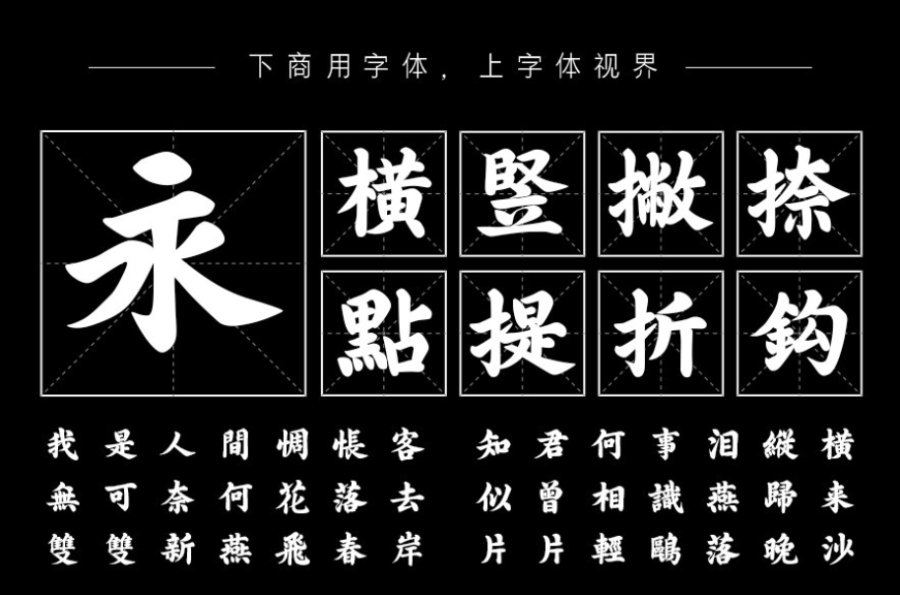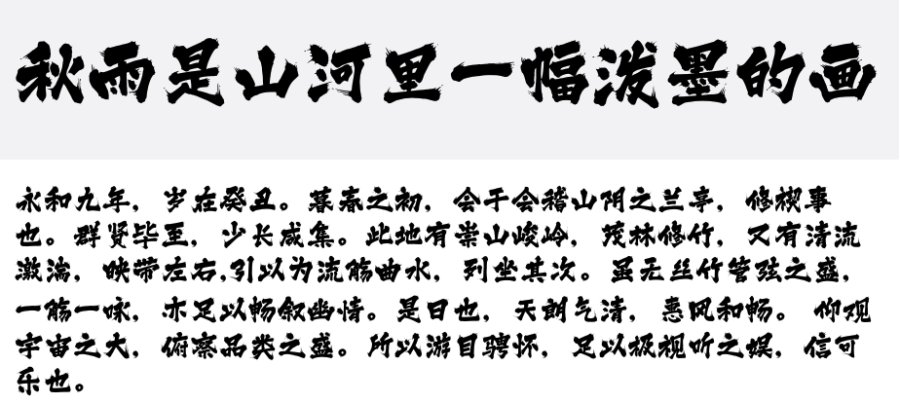
端午节包装字体用什么字体?
每年的端午节活动页设计,你还在为字体素材而发愁吗?中国传统节日的设计大多还是以中国风为主,这里小字推荐的字体也主要也是毛笔字体,希望能给你带来一些灵感。
邯郸朝鲜榜书繁体该字体属于书法大字榜书范畴,其书风结体有度,显磅礴之势。注重曲线的刻画,线条柔美,笔画粗细富有变化,起笔和收笔婉曲而利落,字形丰腴,适用于书籍的封面,以及品牌广告和产品包装设计。
邯郸朝鲜榜书繁体
三极泼墨体是由三极字库出品的一款中文简体字体,该字体墨如泼出,字体感觉气势奔放,释放自我,个性洒脱不羁,追求自由。
三极泼墨体